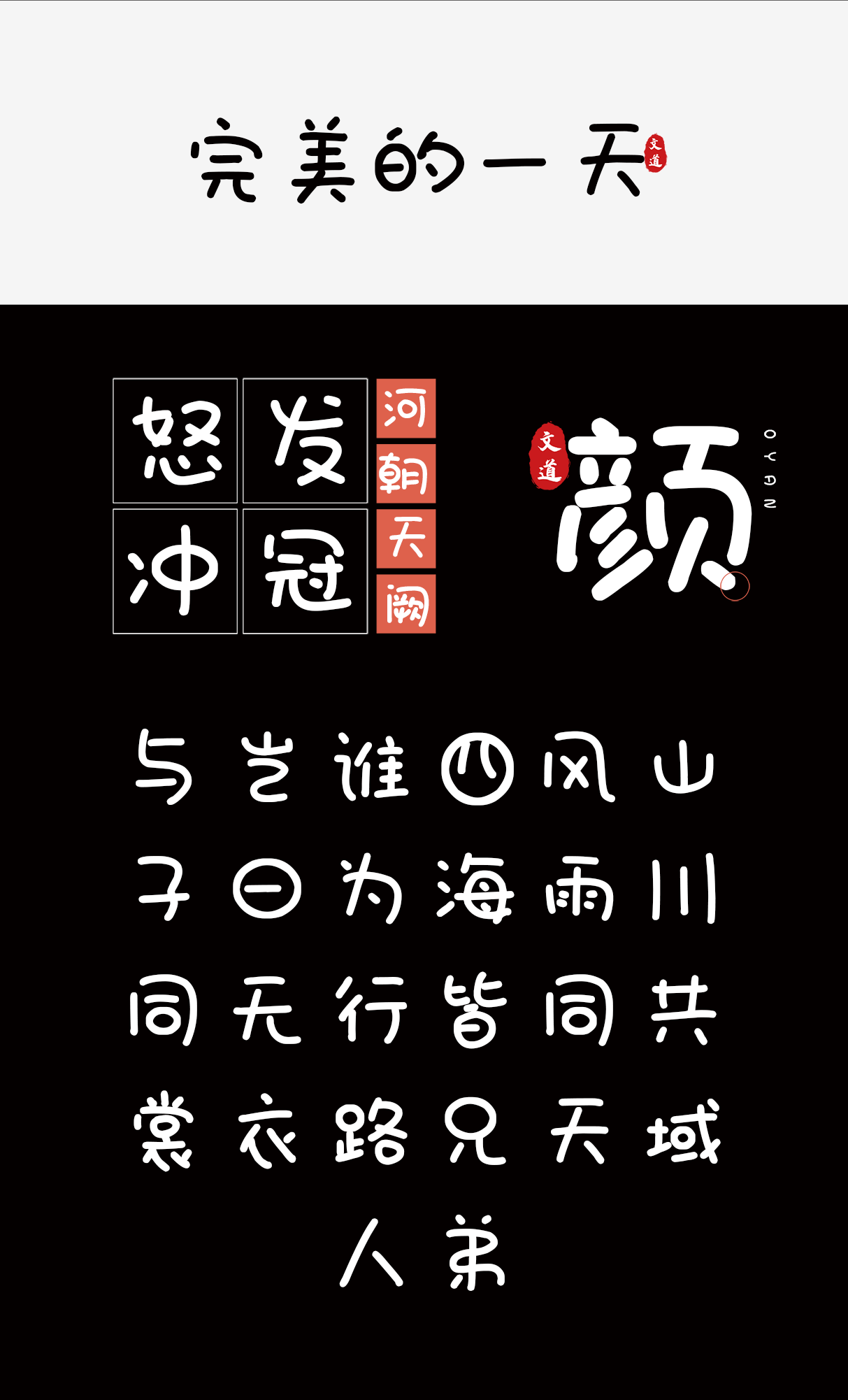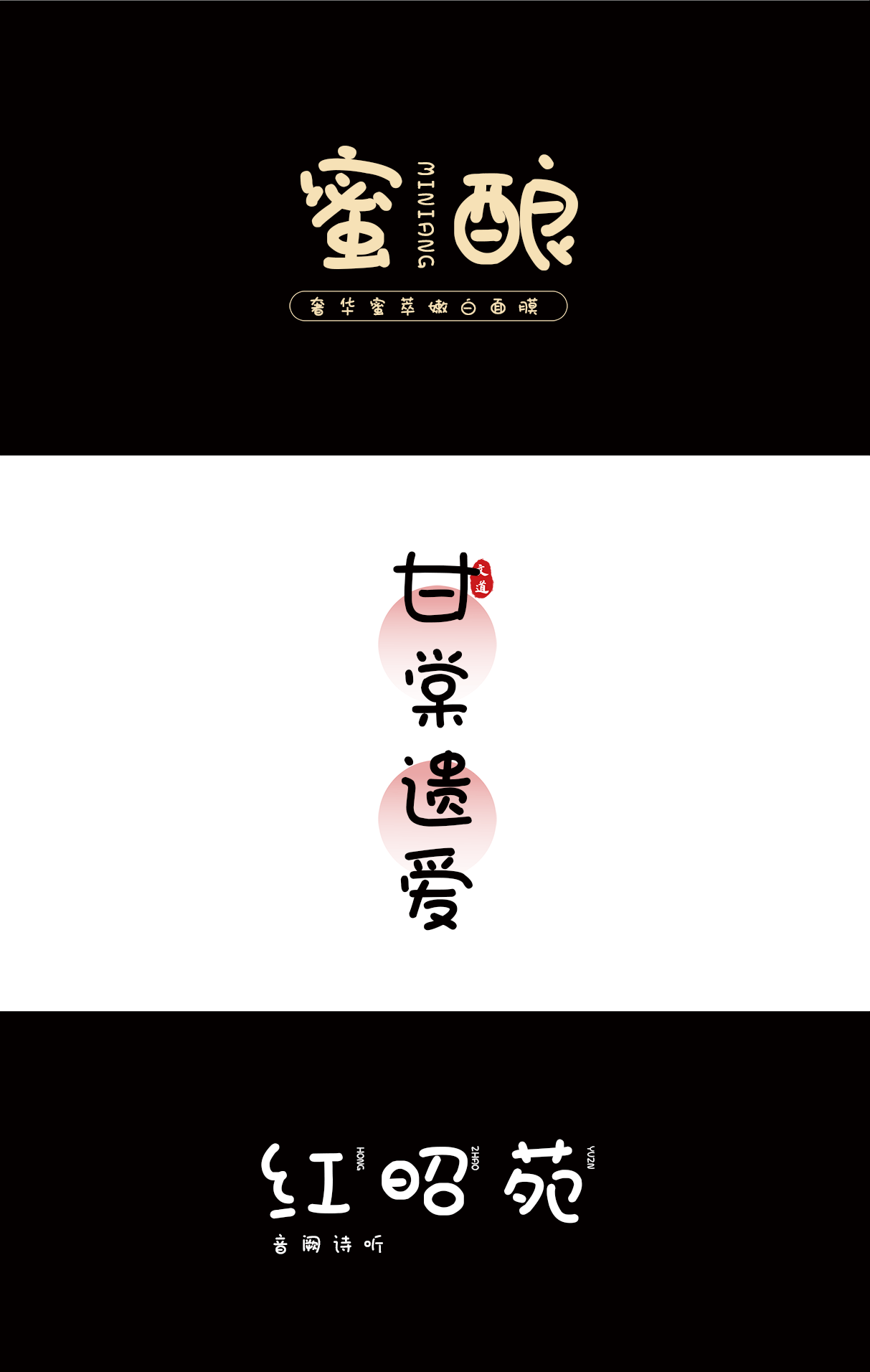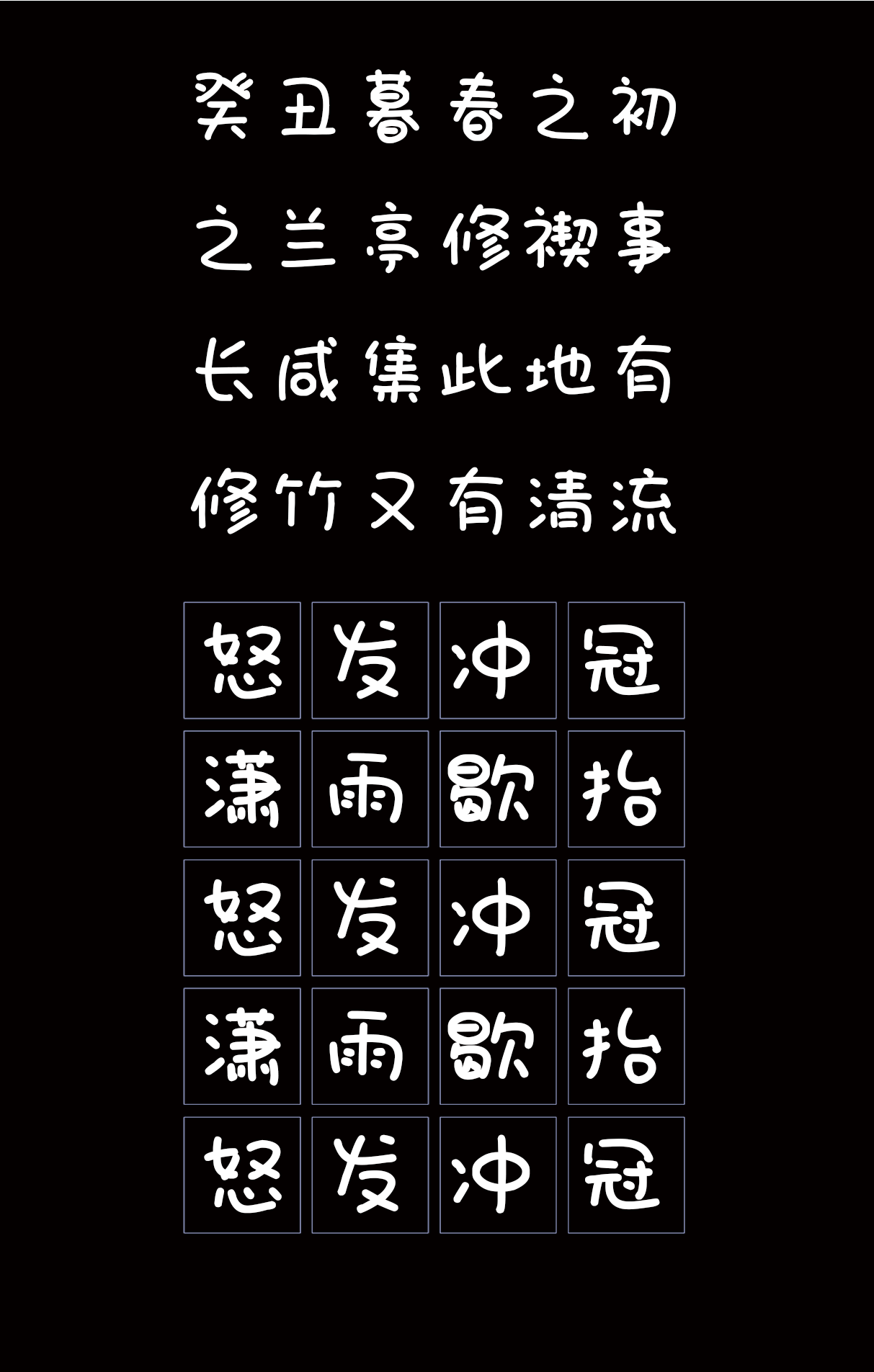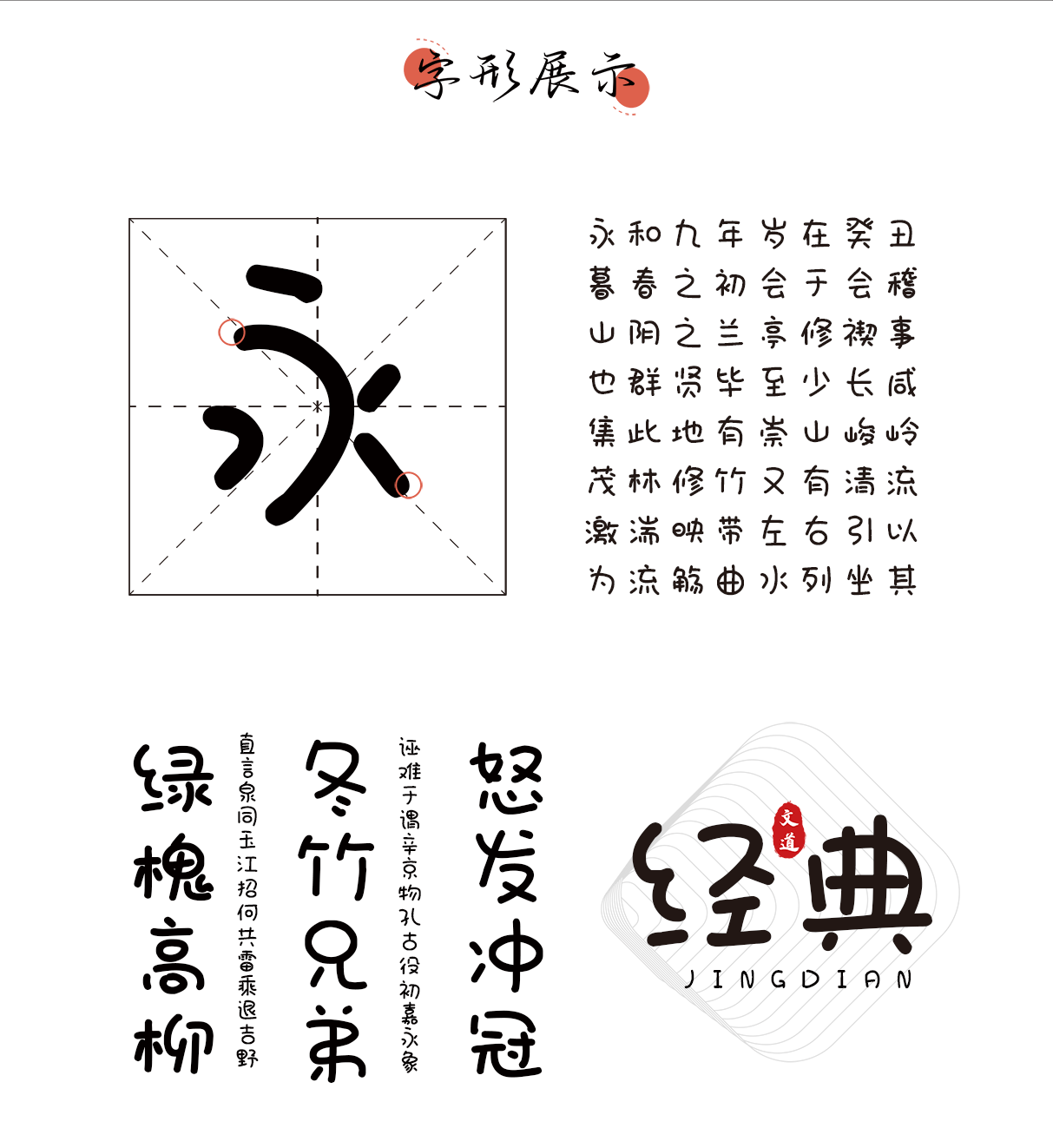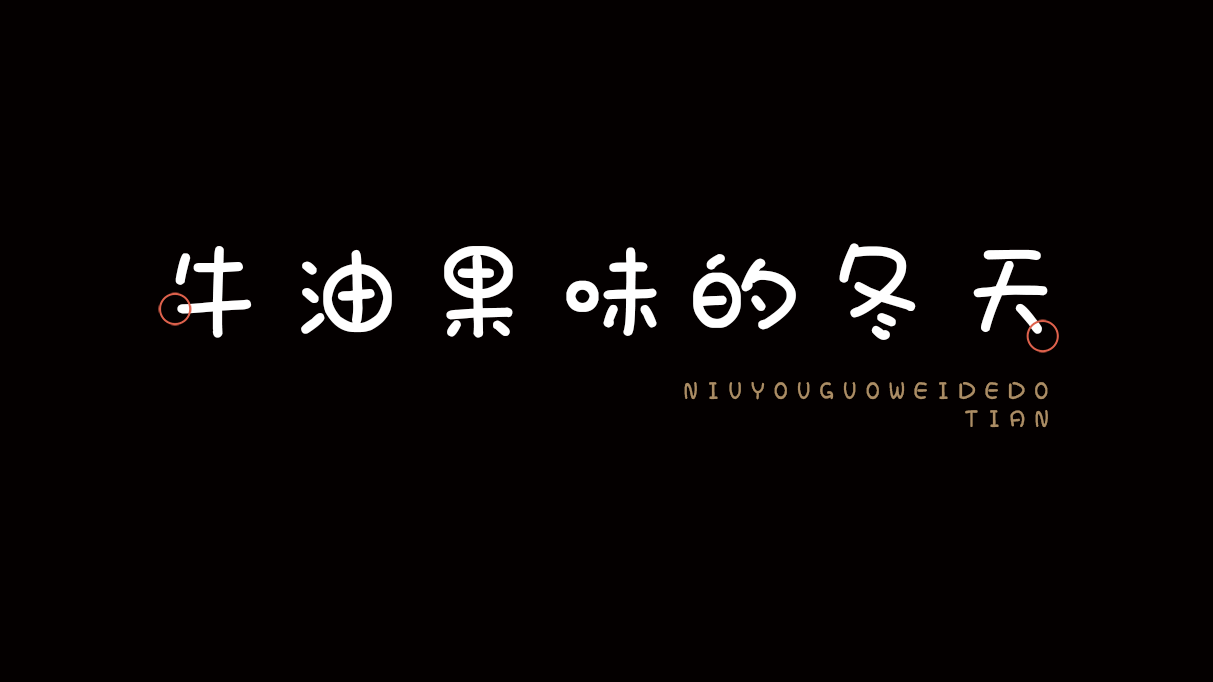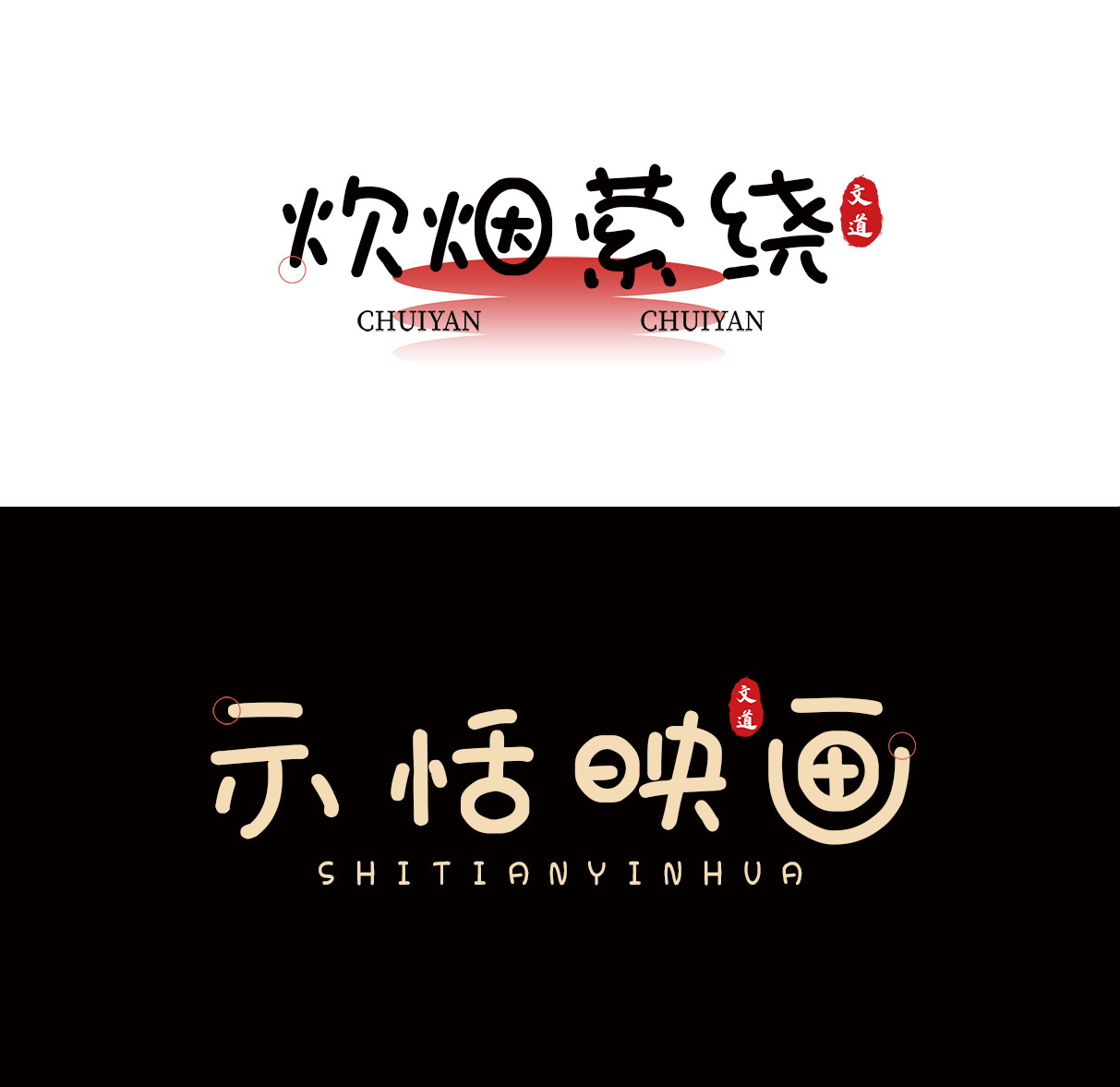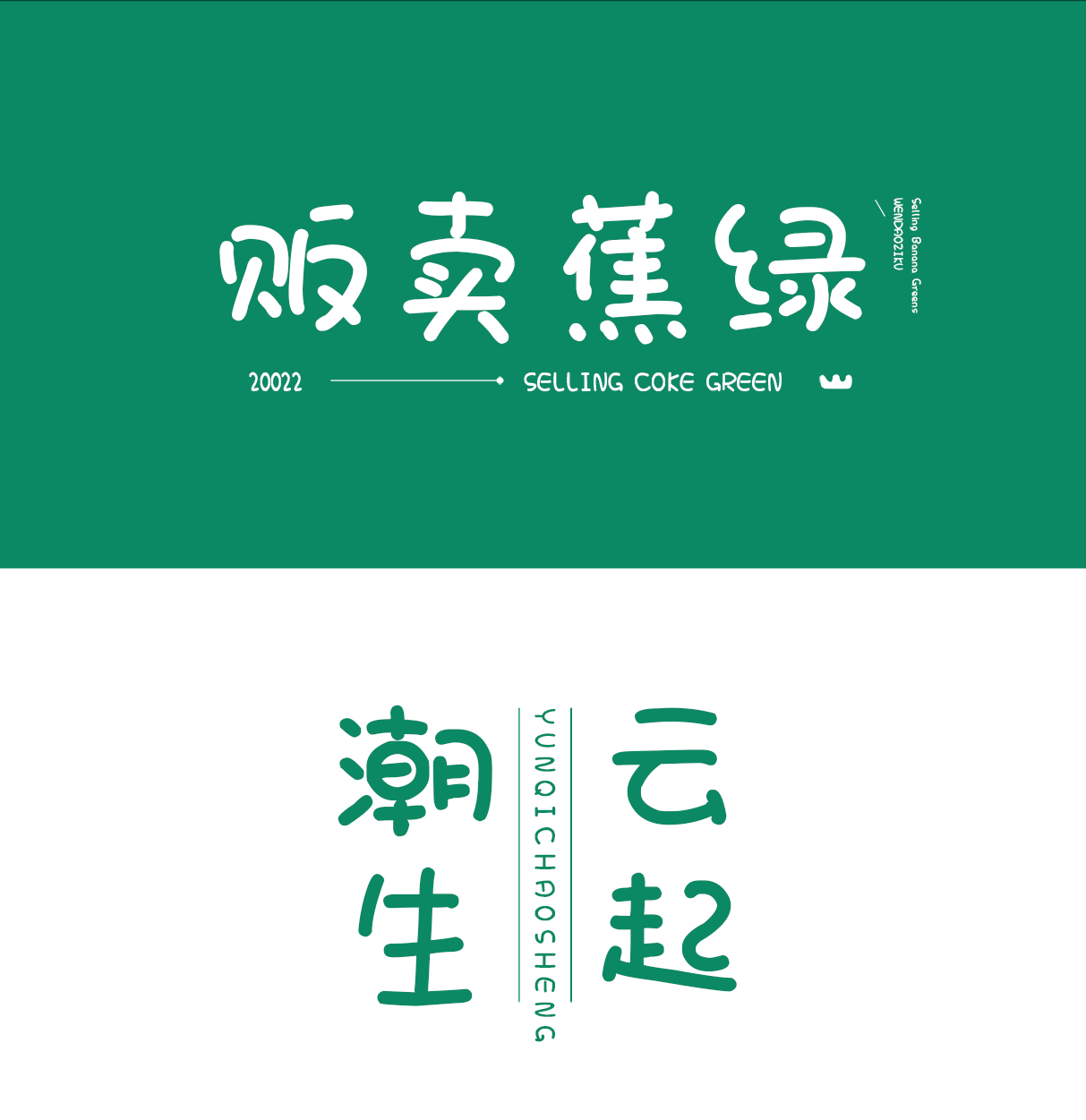
牛油果味的冬天
字体名称: 牛油果味的冬天
所属分类: 创意体 圆体 可爱
简介: 【牛油果味的冬天】这是一款可商用创意体,粗细的笔画加上圆体的设计风格,可爱又非稚嫩的气质凸显而出,该字包含6763个中文、字母、符号和数字,可用于印刷媒介的各类标题,字体风格正好适用于屏幕显示、广告标语和产品类包装设计。